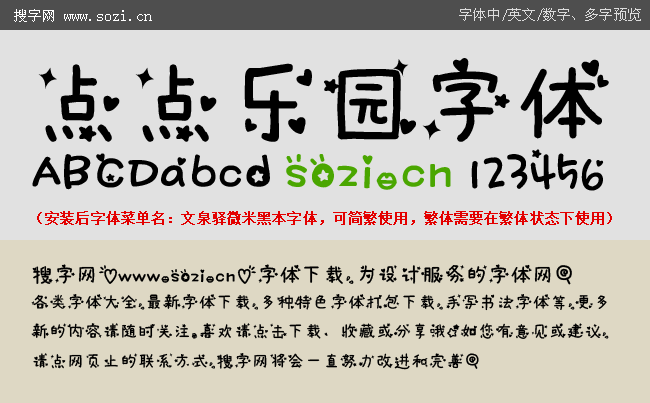
點點樂園字體
搜字網(wǎng)給大家提供一款很可愛的手寫風(fēng)格手機中文字體下載。修改者將它命名為點點樂園字體,這款手機字體是將文泉驛微米黑體的字體風(fēng)格進行了卡通變化。并插入了一些可愛的卡通圖案,將端正的黑體變成了一款非?蓯鄣膬和ㄍㄗ煮w,特別適合小朋友和擁有可愛童心的朋友在手機上安裝使用。